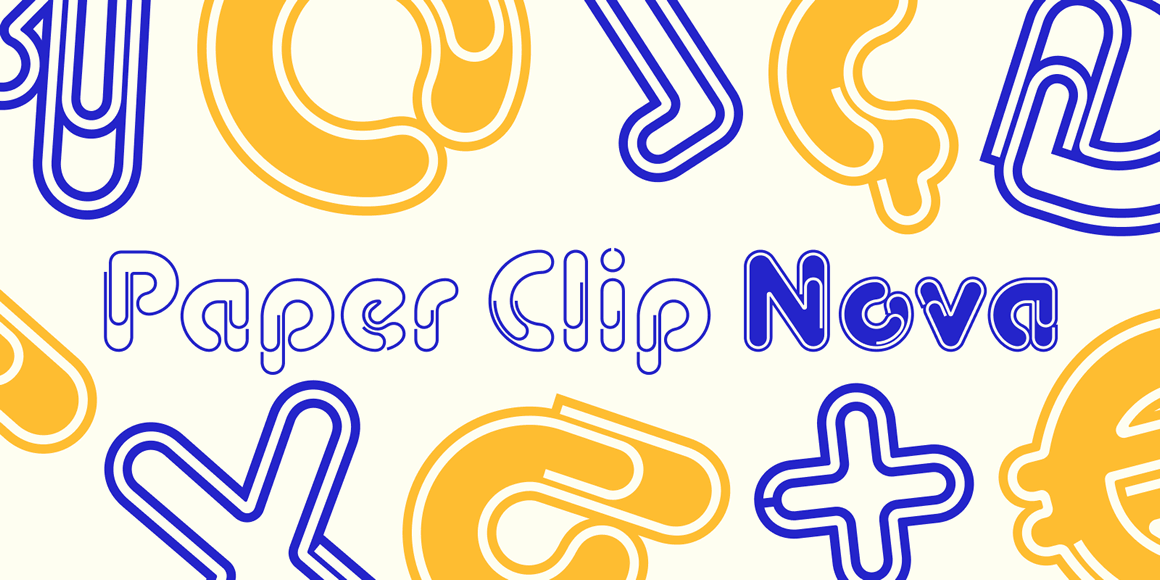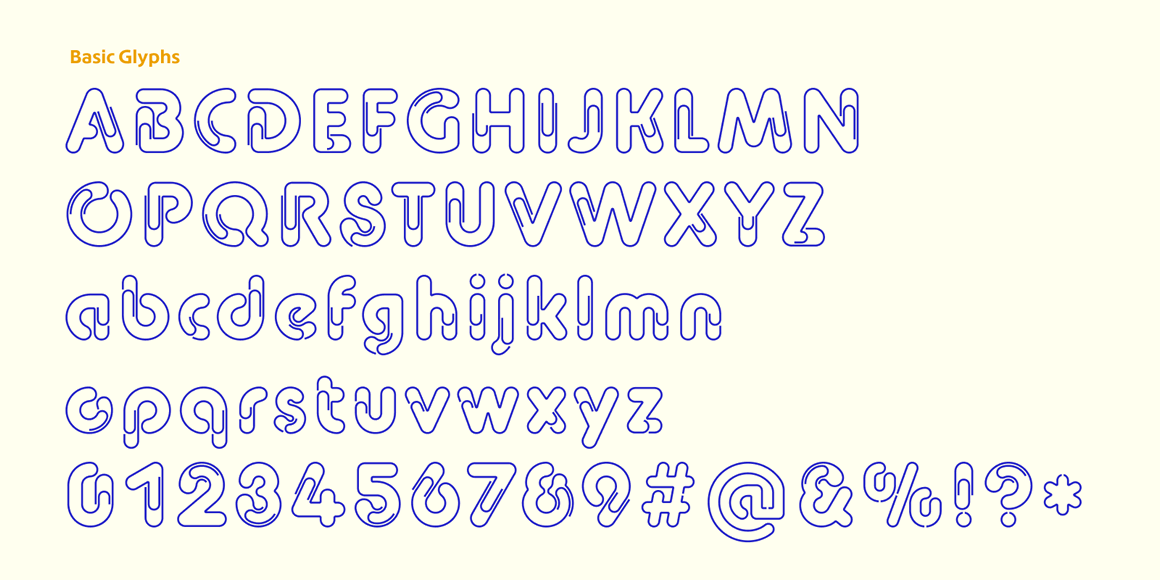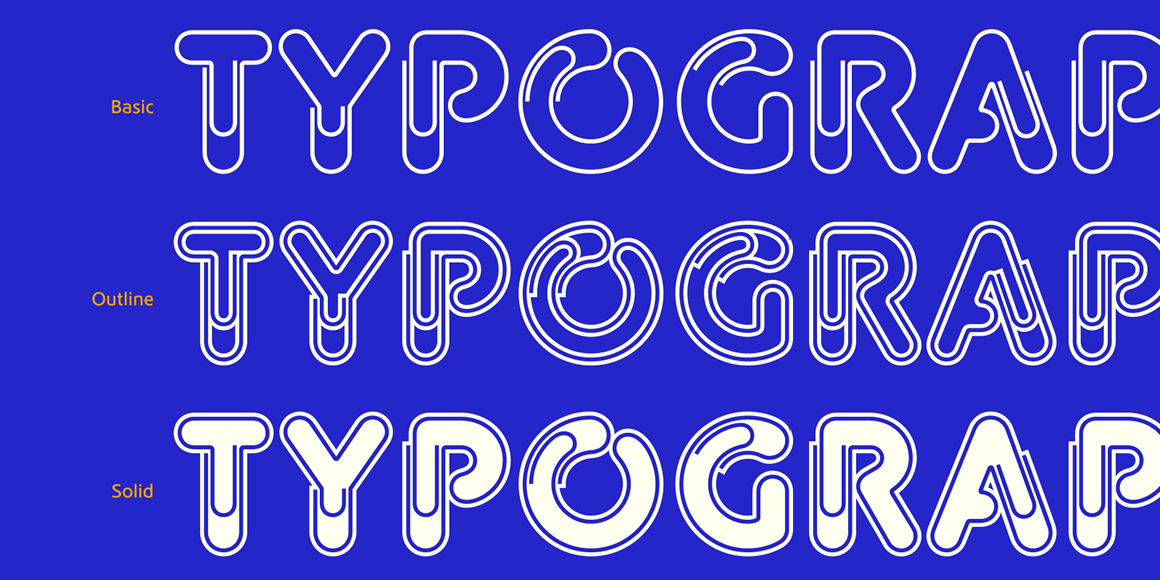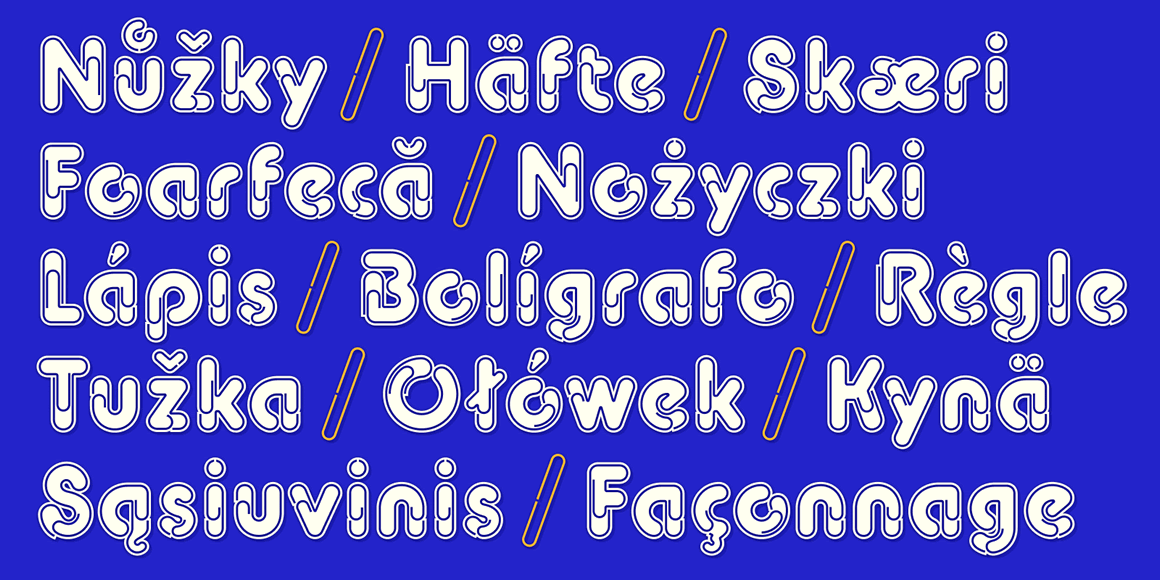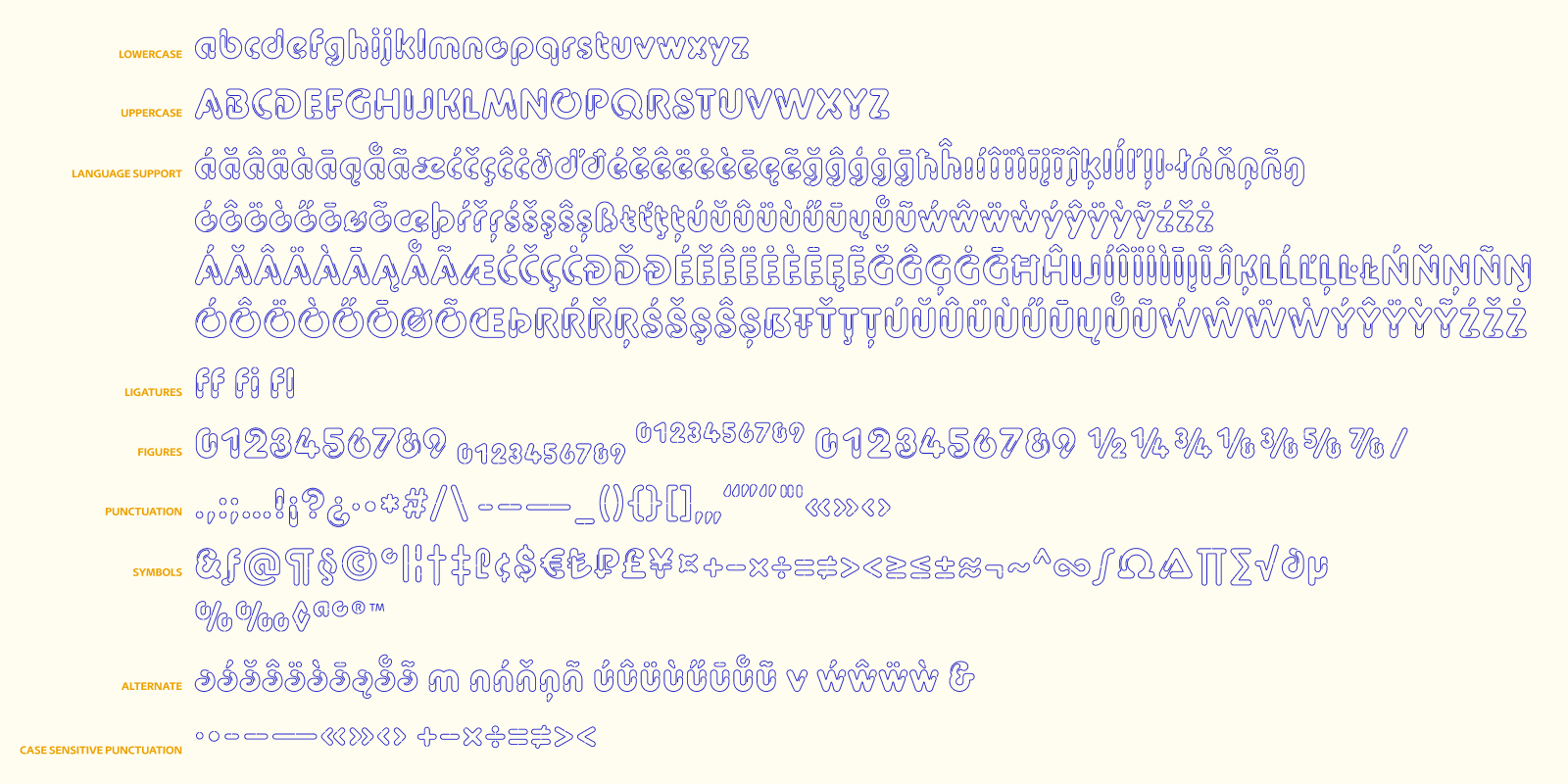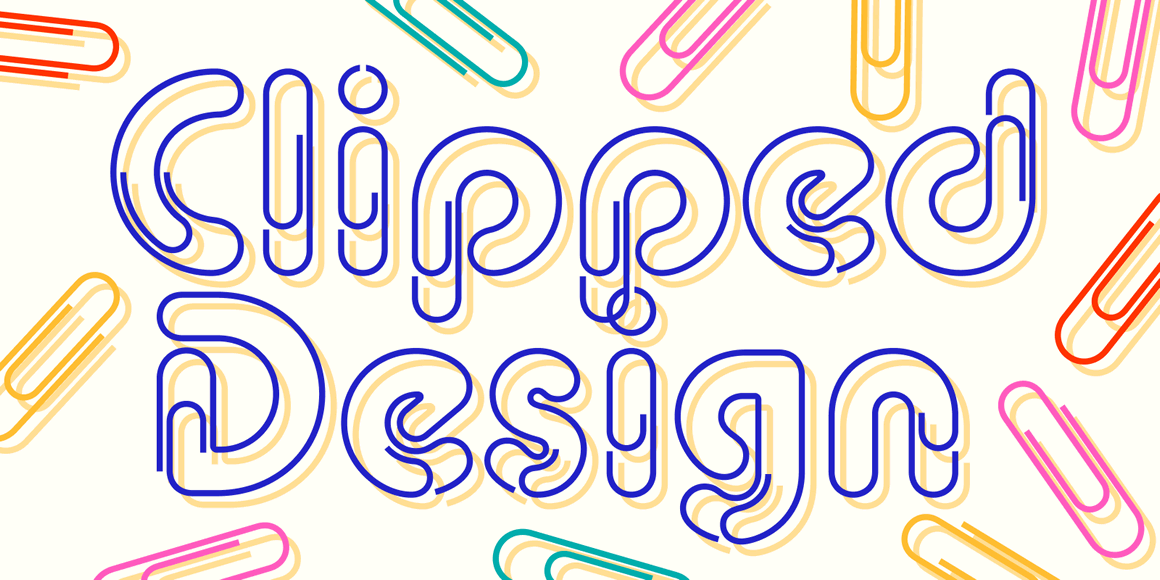
Paper Clip Nova Basic(商品版) |
文具のゼムクリップをモチーフにした見出し用の書体。 その後VGCが消滅してしまい、この書体を使うことはできなくなった…。 2025年、外部デザイナーの協力によって正式に「Paper
Clip Nova」として完成した。 フォントデザイン:佐賀野 宇宙 |
・楽しい・円弧がキレイ・柔らかい・面白い・美しい・新鮮・本物のクリップになる・スゴイ・目立つ・使いたくなる… |
※収容全字種を確認する ・グリフ数 495(Mac OS Roman、Windows-1252、Adobe Latin 3をカバー) ・ヨーロッパ主要32言語以上に対応 アフリカーンス語、バスク語、ブルトン語、カタロニア語、デンマーク語、オランダ語、英語、フィンランド語、フランス語、ゲール語、ドイツ語、アイスランド語、インドネシア語、アイルランド語、イタリア語、ノルウェー語、ポルトガル語、サミ語、スペイン語、スワヒリ語、スウェーデン語。クロアチア語、チェコ語、エストニア語、ハンガリー語、ラトビア語、リトアニア語、ポーランド語、ルーマニア語、セルビア語、スロベニア語、トルコ語、エスペラント語など。 ・OpenTypeフィーチャーにより、大文字用字形、分数表示、化学用上付き下付き数字などに対応。 |